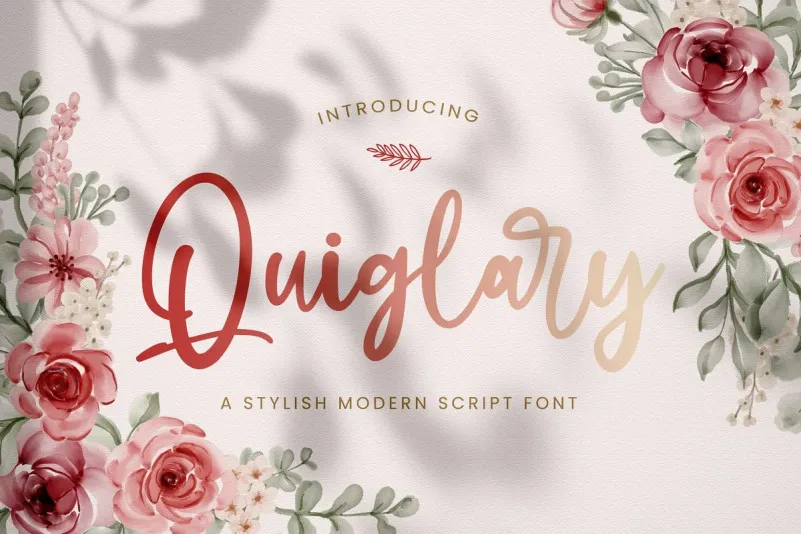
Quiglary Font – Fonte Grátis
Quiglary Font
A Quiglary Font é uma tipografia script moderna e fina que traz beleza e equilíbrio a cada letra. Seu desenho equilibrado permite que se adapte perfeitamente a um amplo leque de projetos, desde ilustrações até design gráfico sofisticado. Esta fonte é ideal para quem busca uma alternativa única e elegante aos scripts mais tradicionais, tornando seus projetos ainda mais interessantes e criativos. Seja você um designer profissional ou alguém que gosta de desenhar por prazer pessoal, a Quiglary Font oferece o acabamento perfeito para dar vida à sua ideia mais original.